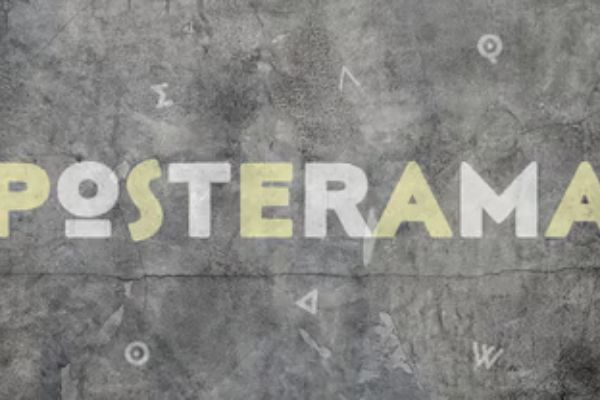
Posterama™ Pro 1984 Thin
Posterama 设定了一种令人回味的风格,参考了艺术、建筑、海报设计和科幻小说领域,将整个世纪的未来主义可视化到一个字体家族中。它具有无限的魅力,可以任意贴合不同的氛围和主题。Posterama 适用于海报、文字商标、标题和副标题等,也可作为交互项目的品牌和显示字体。它具有最强大的字符集,支持泛欧洲语言(包括希腊语和西里尔语)。